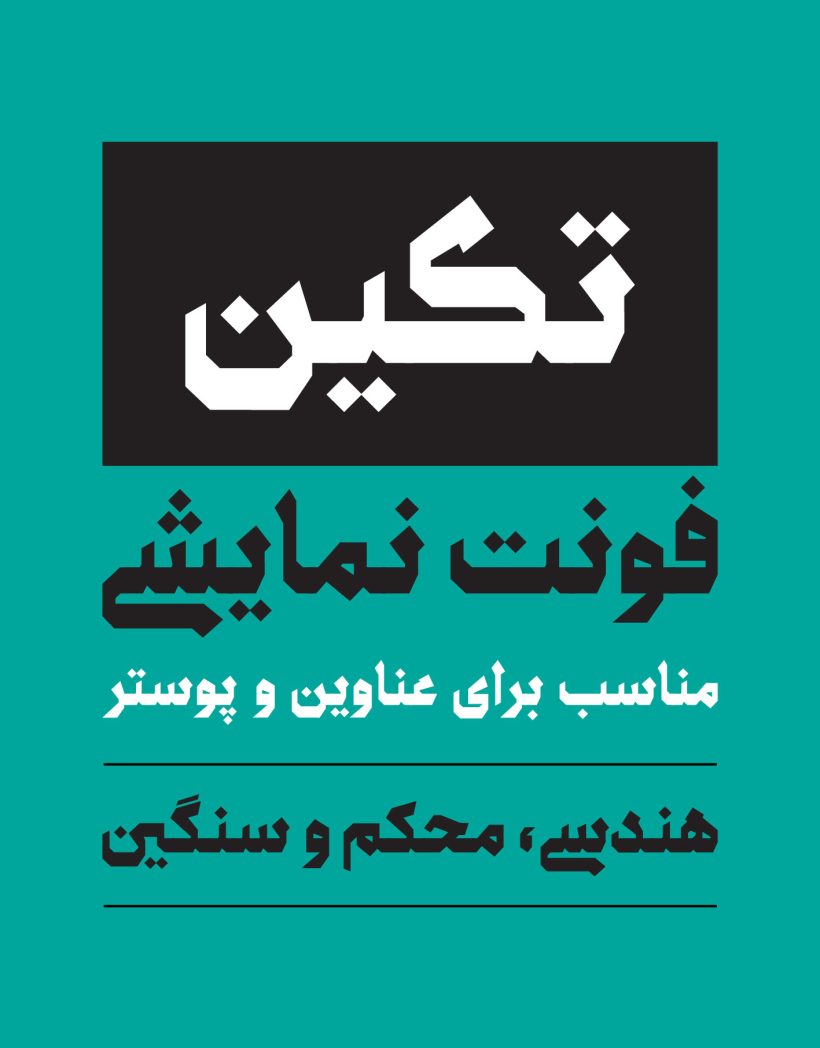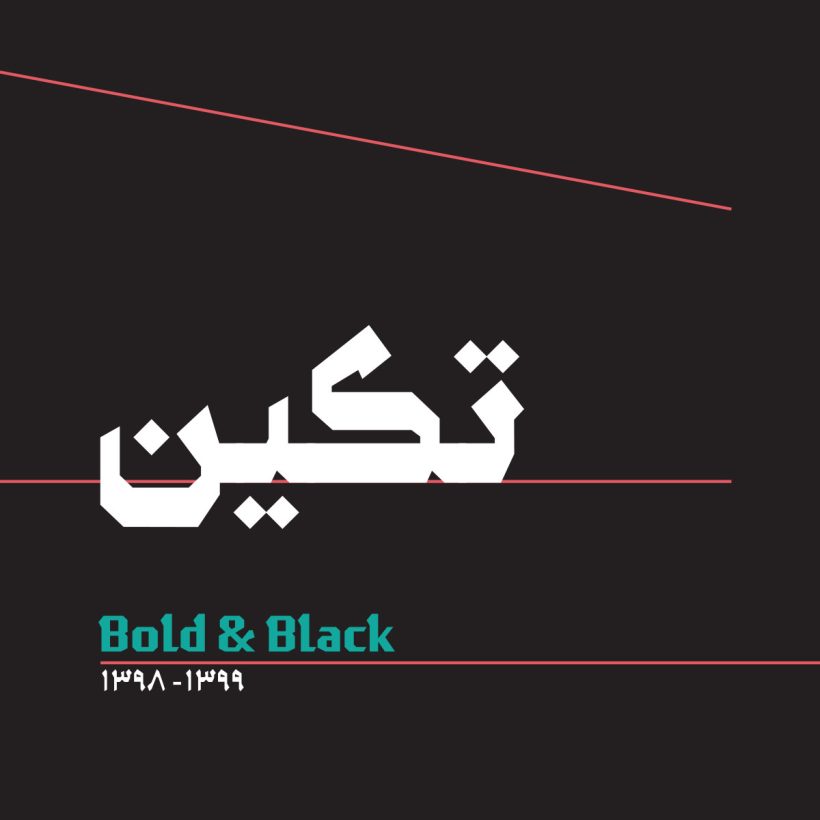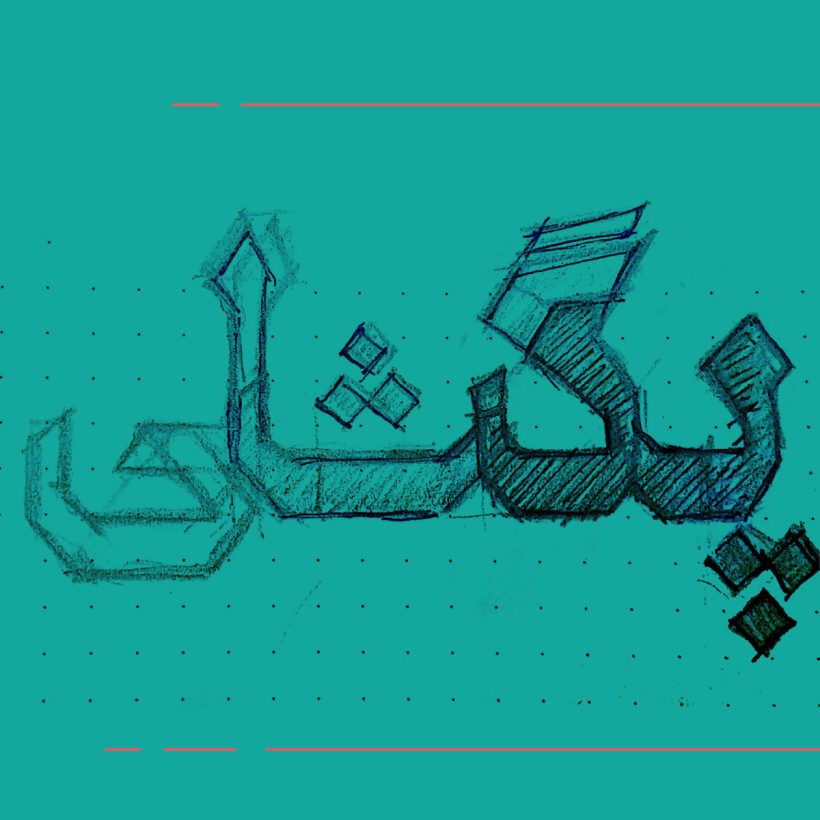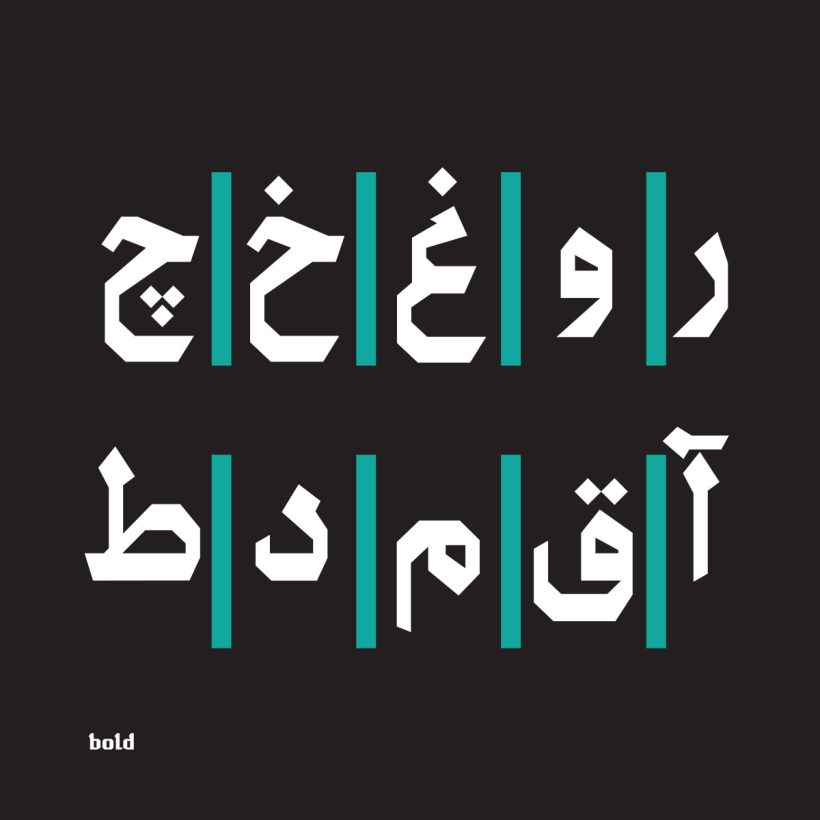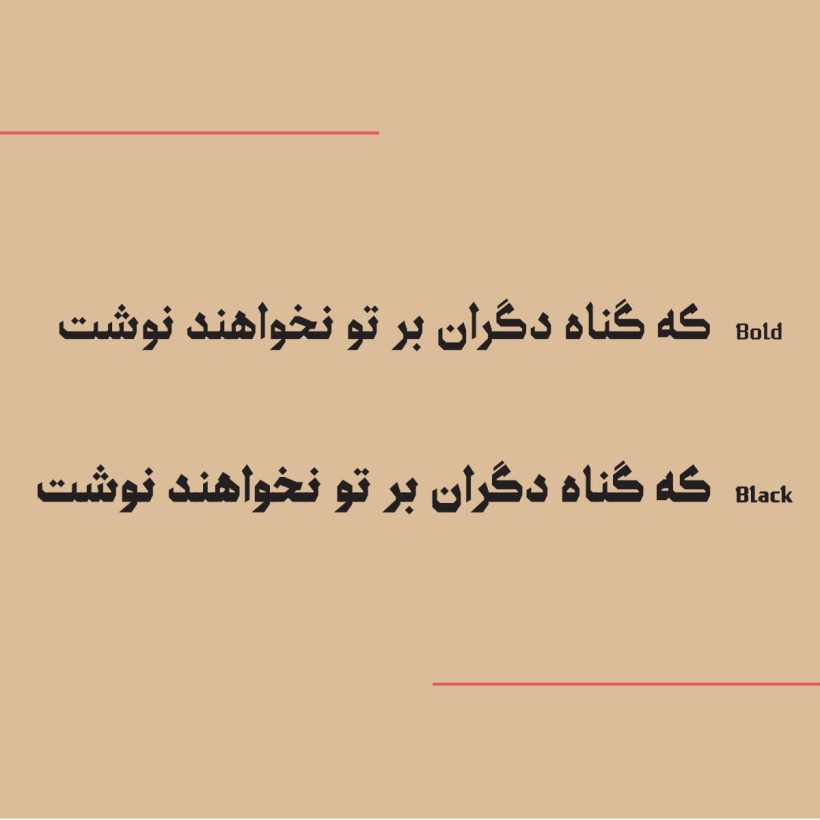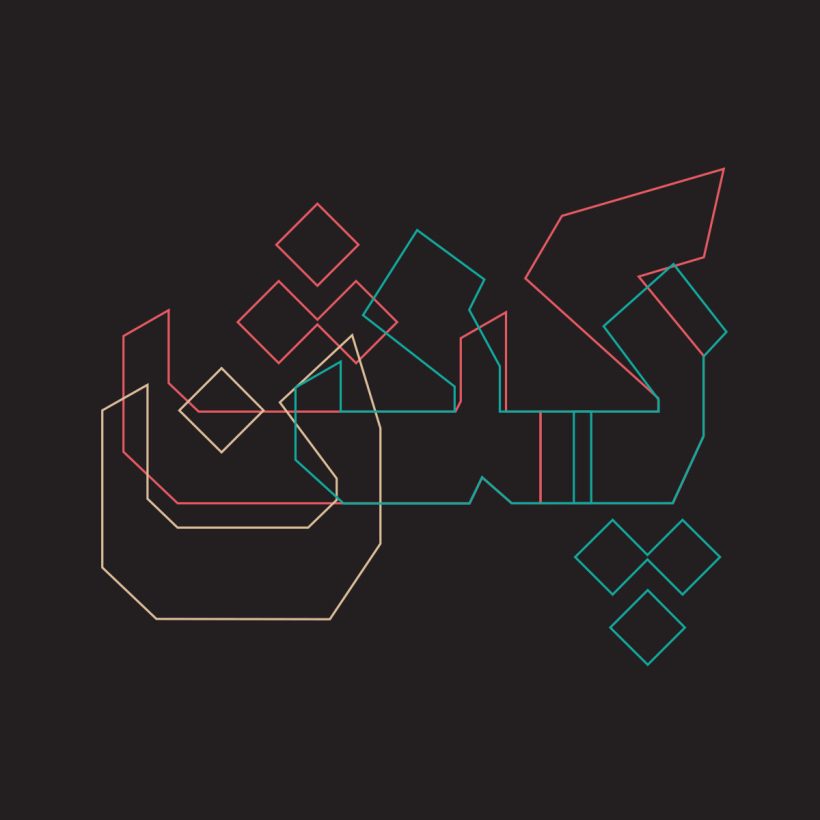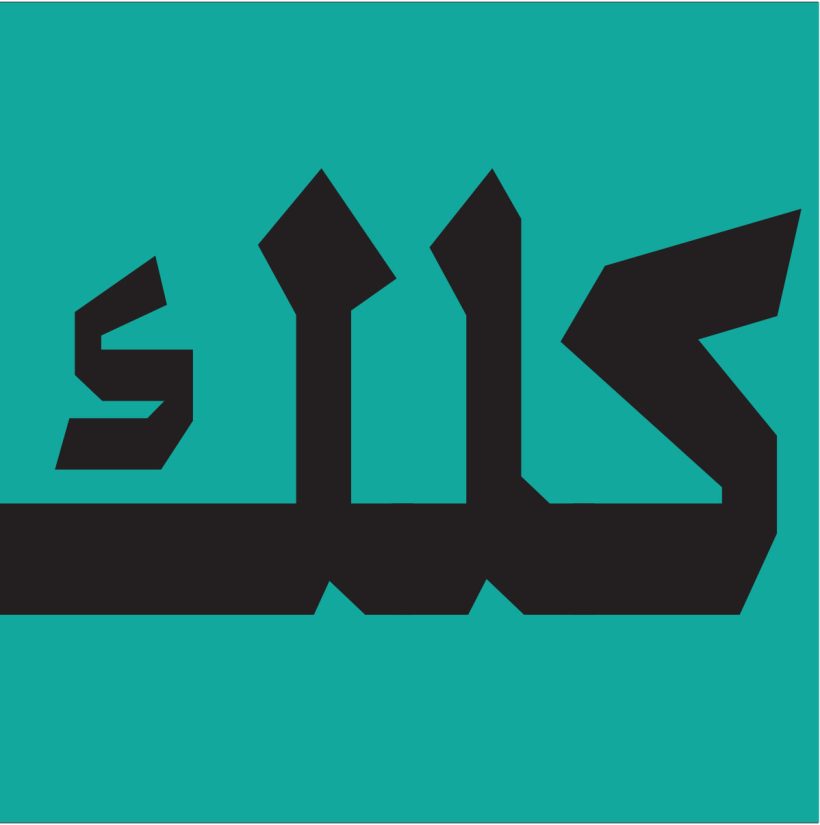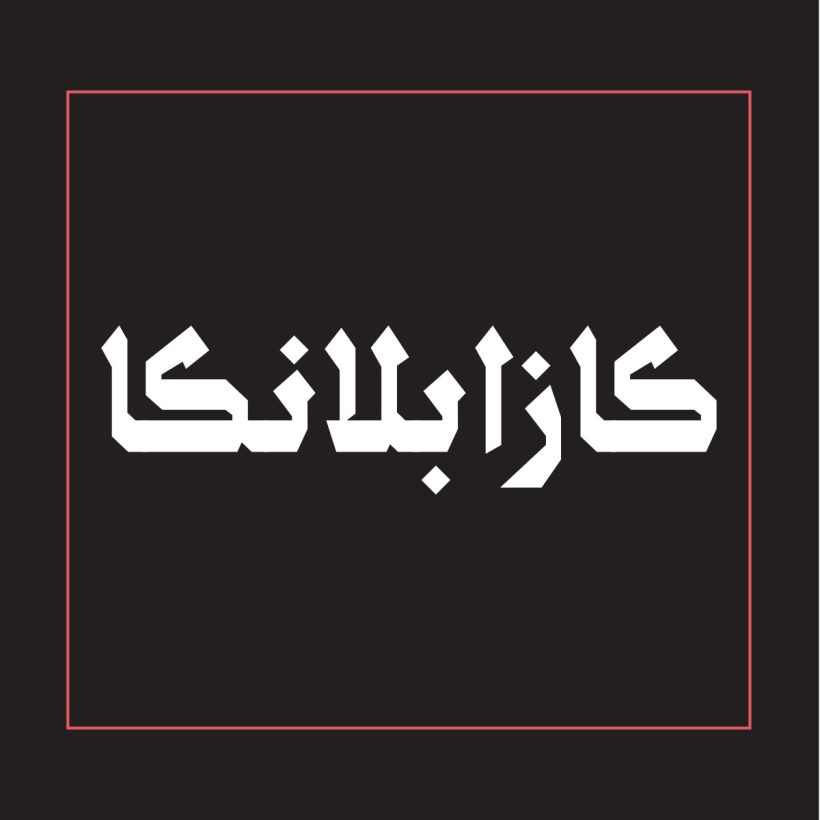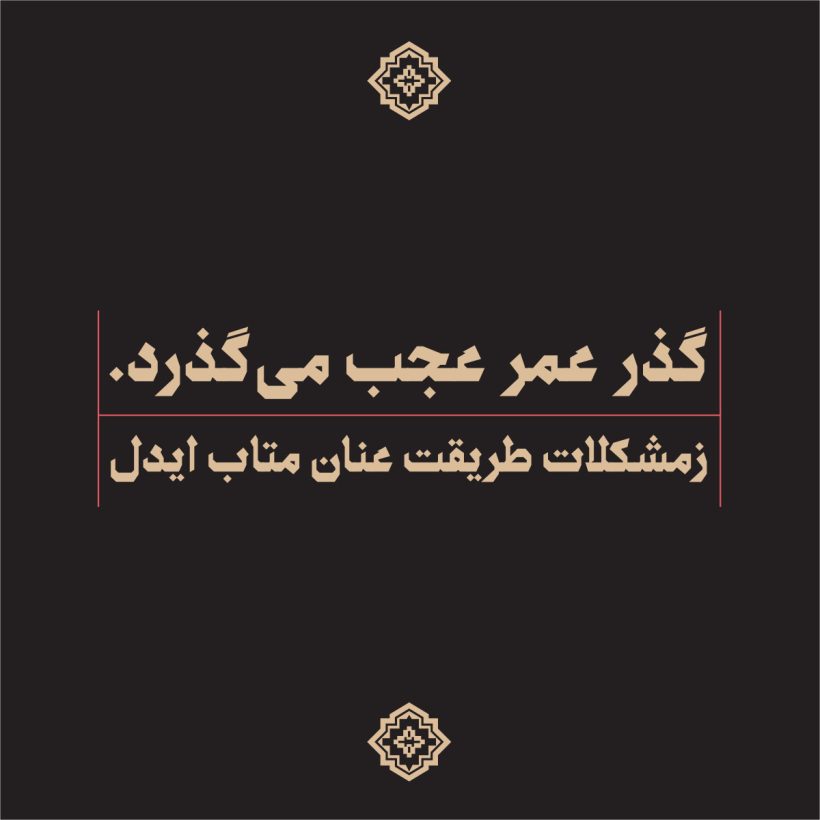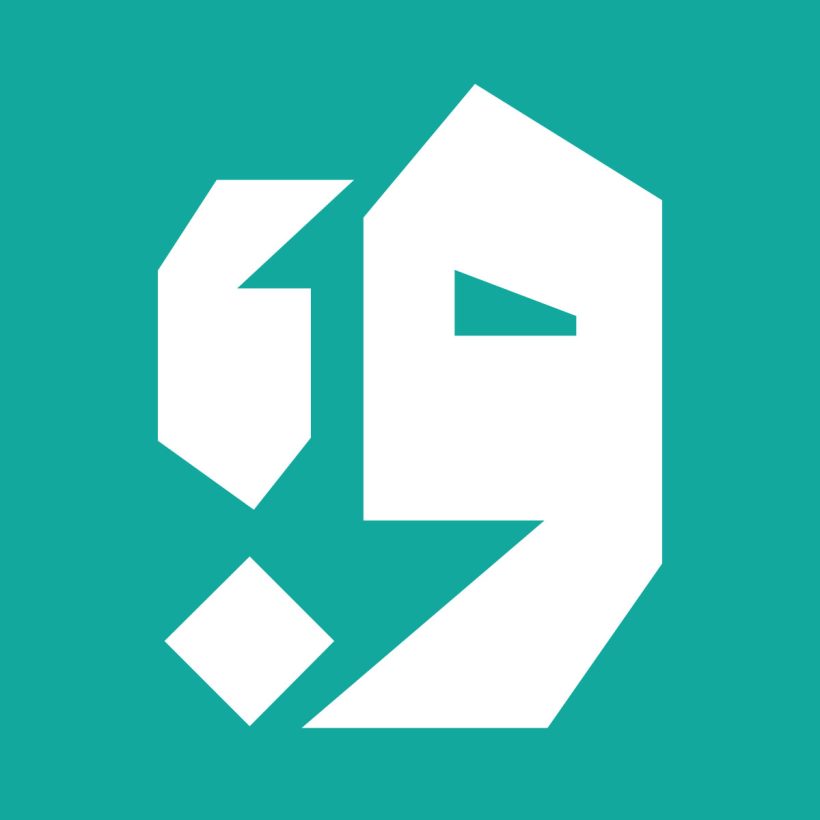
خانواده فونت تکین
لحن فونت تکین، نگاهی نو و جدید به طراحی فونت تیتر و نمایشی است. یکی از کاربردهای فونتهای تیتر در اندازههای بزرگ و برای امور تبلیغاتی است و در این حوزه در یک نگاه باید تا حد ممکن تأثیرگذار و رسا باشد. فونت تکین هندسی، محکم و سنگین است و در عین تنومند بودن، به خوشنویسی سنتی وفادار است. هندسه مشخص و قابل توجهی دارد و دور حروف در آن حذف شده است. در فونت تکین از کمترین فضا برای بیشترین کاربرد و بیان مطلب به شکل مطلوب استفاده شده است. به زیبایی اجزای حروف و کلیت آن به شکل همزمان توجه شده، خصوصیتی که در طراحی فونت تیتر حائر اهمیت است. شکستگی در زوایای استروکهای حروف و کنتراست در پهنا و نازکی مجموع عواملی است که سبب خوانایی و زیبایی این فونت شده است.
تکین در دو وزن بولد و بلک طراحی شده و حروف انگلیسی آن متناسب با حروف فارسی ارائه شده است. قواعد کرنینگ و اعراب گذاری در این فونت به کار رفته است.
فونت تکین توسط معصومه مصلح و صداقت جباری طراحی شده است.